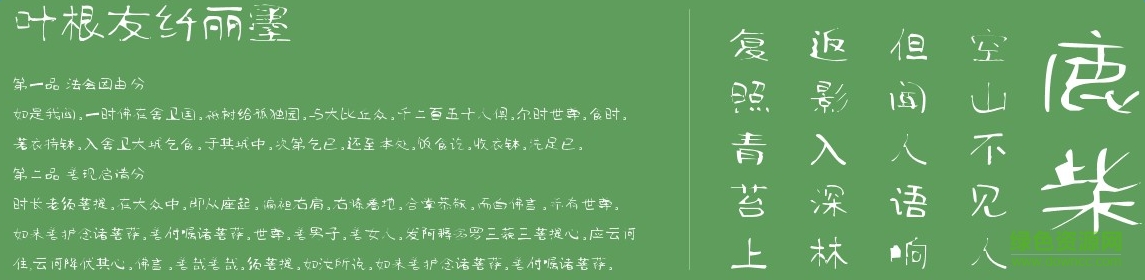
葉根友纖麗墨
葉根友纖麗墨字體是由中國書法奇人,五筆同書世界首創(chuàng)者,連筆空心字吉尼斯世界紀錄保持者葉根友先生親自書寫的一款字體,是葉根友先生平時書寫最多的一種,也是最為實用的風(fēng)格。字體大方,流暢。歡迎下載!
葉根友纖麗墨是一款輕松自在的中文簡體字體,該字體非常具有卡通形象,讓各位用戶能夠在使用時,不失了童心,非常有趣,歡迎來綠色資源網(wǎng)下載使用!